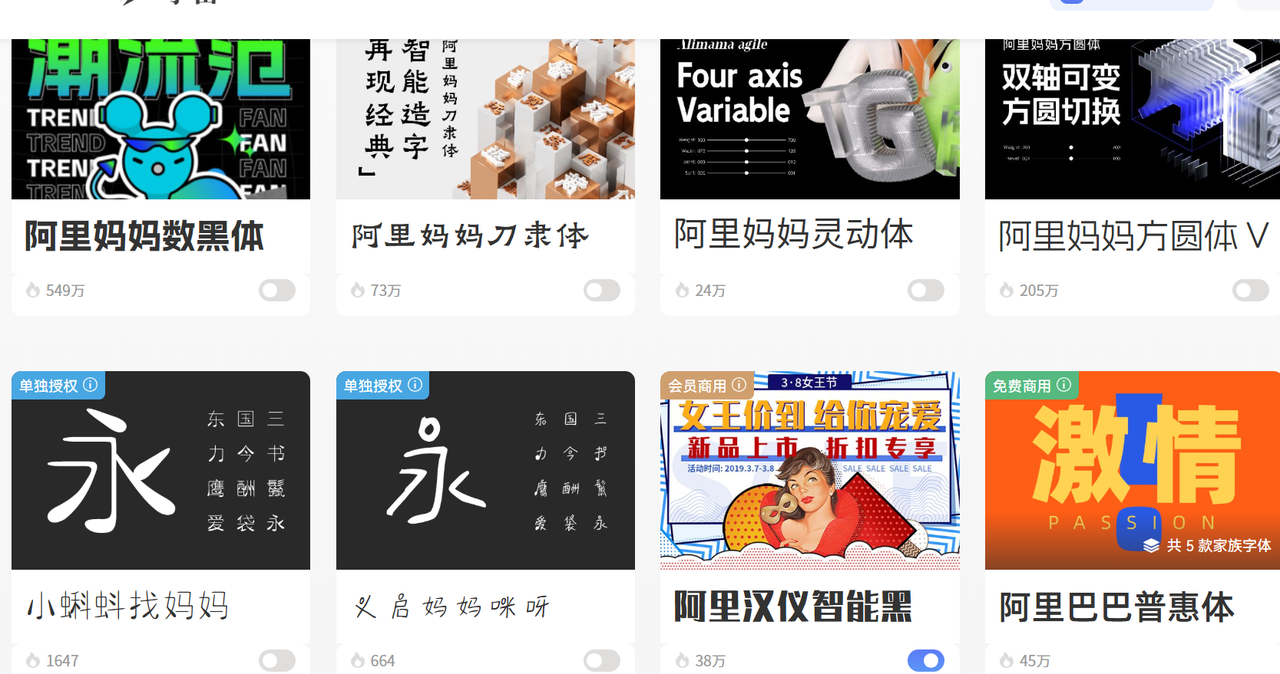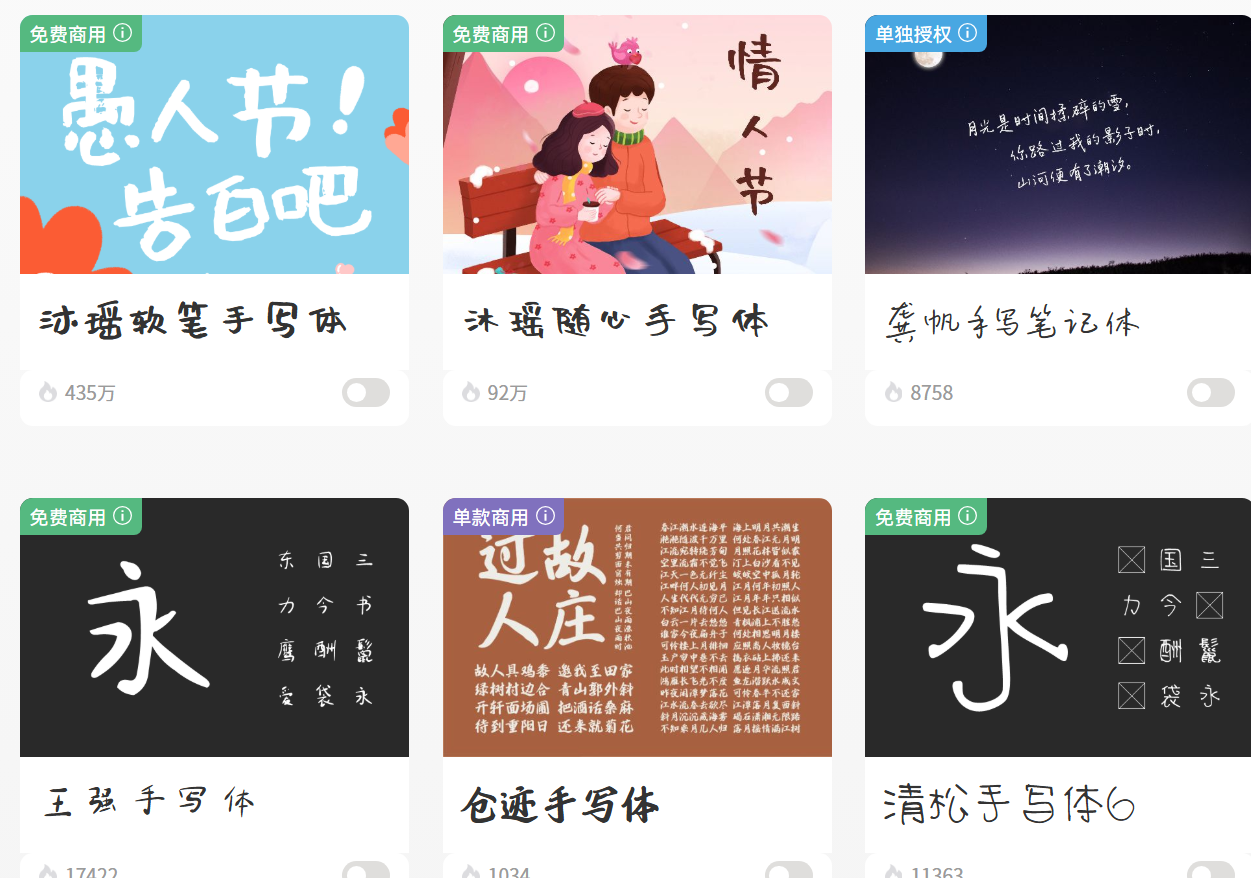
别再乱找了!4个Windows 字体下载网站推荐
如今日常办公和设计创作中,字体的选择愈发重要,一款合适的字体能让文档更精致、设计作品更出彩,Windows 系统用户常常苦于找不到优质又安全的字体下载渠道,我也曾为筛选靠谱的字体网站反复摸索,本文就给大家推荐 4 个实用的 Windows 字体下载网站。
1. 字由网
作为常年用Windows做设计的老用户,字由网是我电脑里常年收藏的Top1字体网站,也是最推荐给新手的一个windows字体下载网站——它完美避开了多数字体网站的痛点,而且适配所有Windows系统(Win7/10/11均支持)。字由网的字体资源非常丰富,不管你是办公、设计还是娱乐,都能精准找到对应字体。
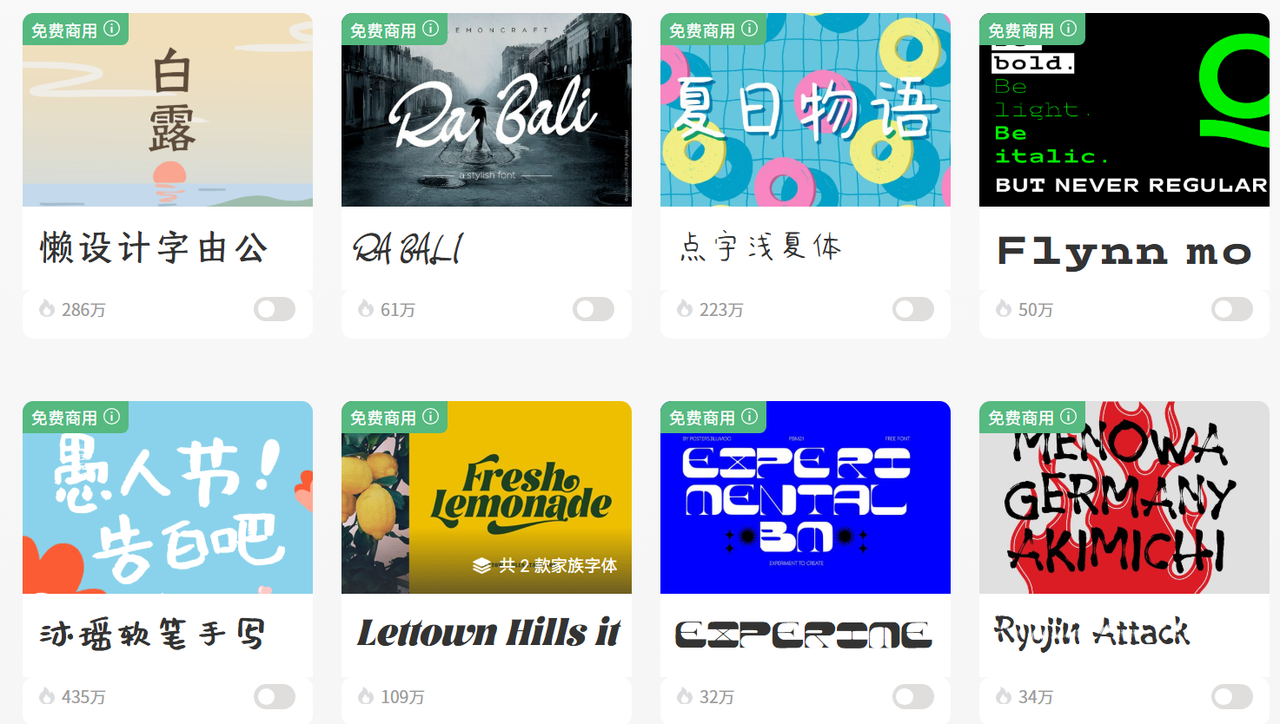
对我而言,阿里妈妈数黑体是Windows办公首选字体,适配Word、Excel、PPT等所有办公软件,不管是正文排版还是表格填写,都显得干净利落,而且在字由网也是支持免费商用。
还有免费商用的沐瑶软笔手写体,这种温柔治愈的手写体我一般会在制作电子手账的时候用到,适配Windows所有版本。
还有很多款windows字体大家可以自己慢慢挖掘,最贴心的是每款字体都会明确标注“单款商用”“免费商用”“需授权商用”,避免大家误用水印字体、侵权字体,不管是个人办公还是商业设计,都能放心使用。
另外,它还有一个实用小功能:字体预览。在页面的左上方输入自己想展示的文字,就能实时查看该字体的显示效果,还能调整字体大小,提前判断是否符合自己的需求,不用下载后才发现不合适,大大节省时间。
2. 100Font
如果你的核心需求是免费商用字体,尤其是做新媒体、海报设计、短视频字幕,那100Font绝对是不二之选,它的定位就是“专注免费商用字体”,适配Windows全系统,性价比拉满。它的字体种类不算最丰富,但每一款都是精选,和字由网相比,缺点是小众字体较少,追求个性化小众字体的朋友,可搭配其他网站使用。
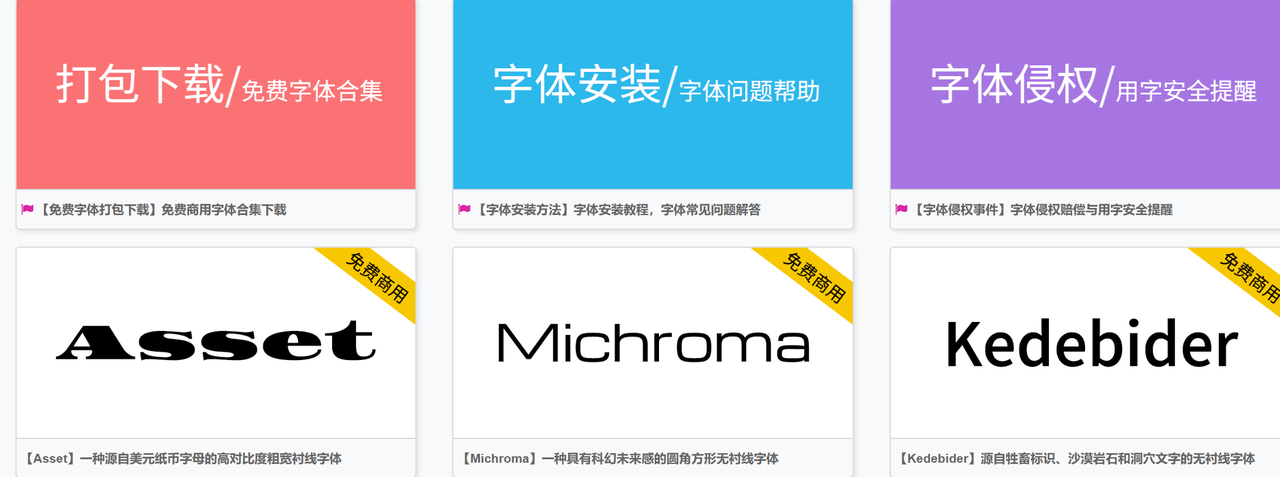
3. DaFont(小众个性首选,英文字体宝藏)
DaFont是一个国外的windows字体下载网站,虽然界面是英文,但操作简单,适配Windows系统,最大的优势就是小众、个性,尤其是英文字体,适合追求独特风格、想摆脱同质化字体的朋友。它支持Windows常用的TTF、OTF格式,适配Win7及以上系统,不会出现兼容问题;需要注意的是,部分字体仅支持个人免费使用,商用需授权。
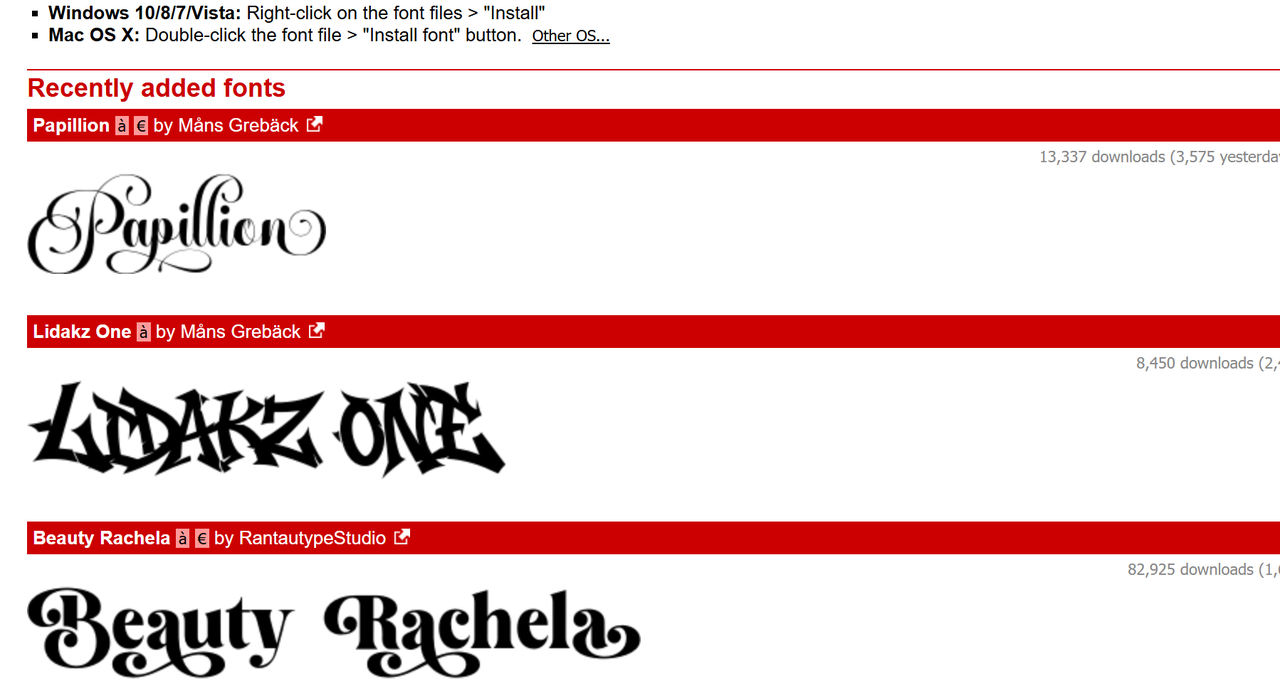
4. 猫啃网
如果你偏爱手写体,那猫啃网绝对能满足你,它是国内专注手写体的适配Windows全系统字体网站,风格温柔治愈,实用性拉满。在每款字体上都会标注是否为免费商用字体,而且它的界面干净简洁,分类清晰,可按“手写体风格”“是否商用”筛选,找字体效率很高。